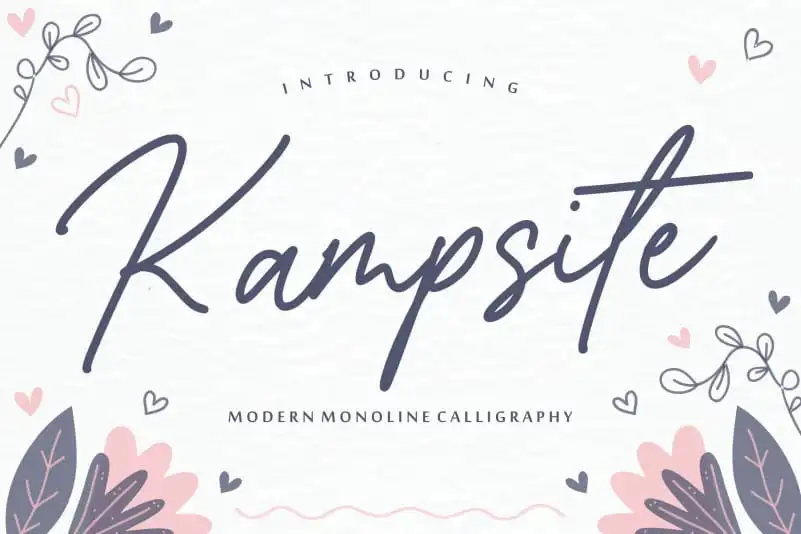
Aqui está uma descrição envolvente para a página de download da font ‘Kampsite Monoline Script Font’: Para quem busca uma fonte moderna e elegante com linhas simples, apresentamos Kampsite Monoline Script Font. Esta chamada à arte é perfeita para projetos variados que necessitam de um toque sofisticado e minimalista. Perfeito tanto para embalagens de produtos quanto para marcas criativas, Kampsite se destaca por sua elegância moderna em qualquer aplicação. Ideal para revistas, redes sociais, editoriais e até mesmo para anúncios de casamentos, essa fonte simples mas poderosa pode fazer uma grande diferença no seu projeto. Ideal tanto para expressar palavras em um fundo sólido quanto para criar elementos visuais intrigantes. Seja qual for o seu objetivo, Kampsite Monoline Script Font certamente ajudará a destacar sua mensagem e torná-la ainda mais memorável.